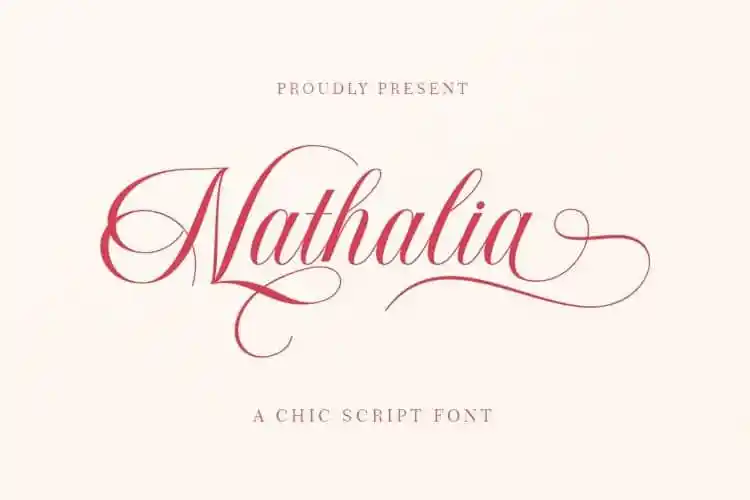
Nathalia Calligraphy Font – Fonte Grátis
Nathalia Calligraphy Font
Nathalia Calligraphy Font é uma fonte de script que chama a atenção com seus detalhes elegantes e alternativas de letras únicas. Desenvolvida pela Romie Creative, esta fonte é perfeita para um estilo de escrita casual, mas também belamente elaborada, ideal para aqueles momentos especiais como casamentos. Seu charme em formações que se abrem permite uma variedade inestimável de usos, desde o branding, os selos até as capas de livros e as postagens na rede social. Com apenas um clique da sua teclada, transforme qualquer design ou projeto com a sofisticação única desta fonte. Não perca tempo, descubra agora como Nathalia Calligraphy pode revolucionar o seu próximo trabalho!